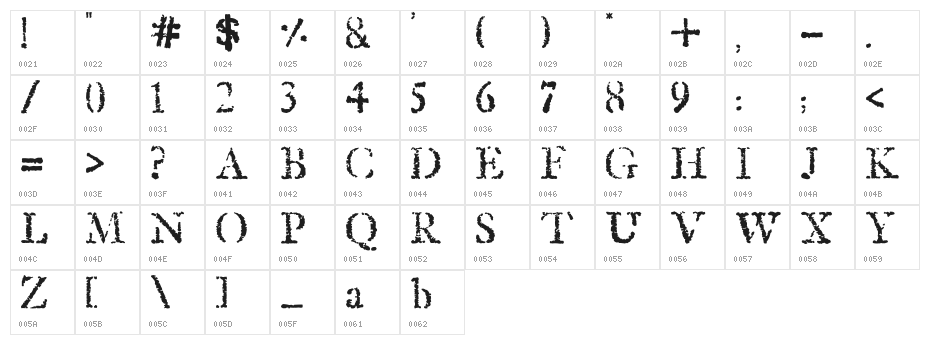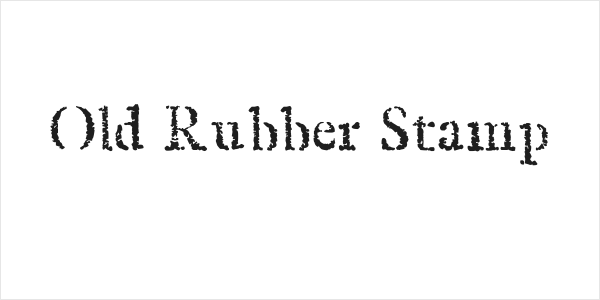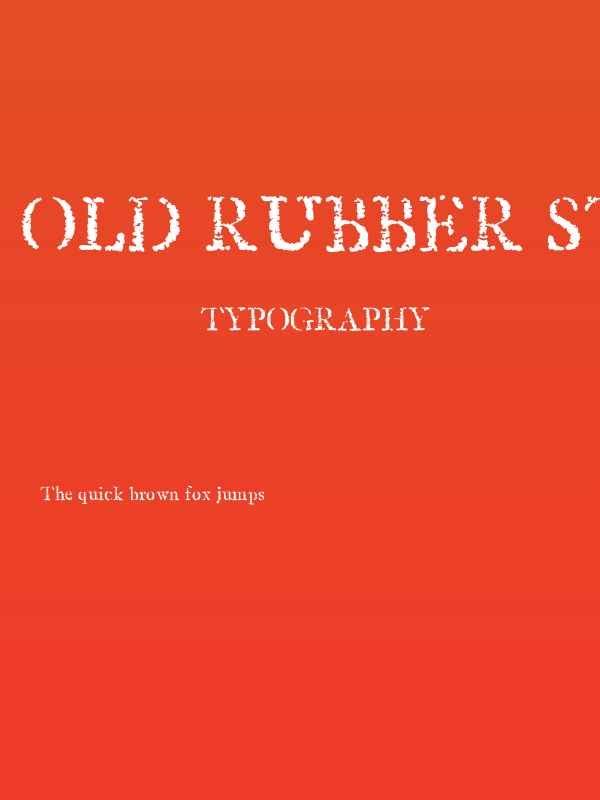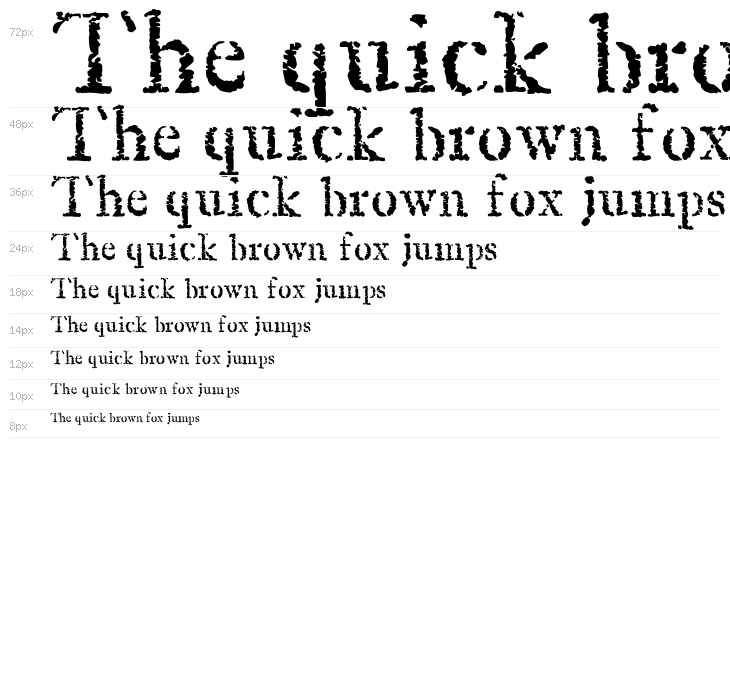
Old Rubber Stamp Font
| Категория | Distorted Eroded |
| Общий стиль | Vintage |
| Рекомендуемые проекты | Ideal for vintage-themed designs, posters, branding, and packaging that require a rustic or industrial touch. |